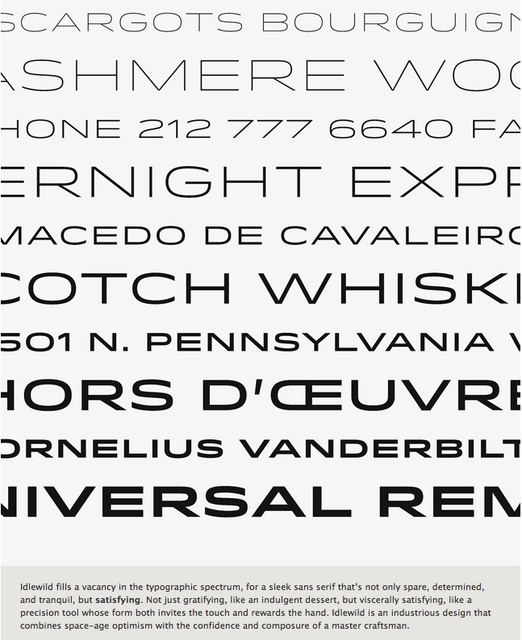
New Fonts from H&FJ: Idlewild
Außerdem finde ich es bedauerlich, das sie in Sachen Open Type Features auch nicht recht mit der Zeit gehen. Diesbezüglich sind die Schriften leider nur sehr schwach ausgebaut. Es gibt kaum alternative Buchstaben, geschweige denn Ziffernsätze etc. Und wenn bei der Idlewild unter Features neben der Sprachunterstützung lediglich andere Schriften zur Kombination angepriesen werden, ist das ja selbstredend.
Schade, denn ihre Schriften sind formal wirklich toll.
Außerdem finde ich es bedauerlich, das sie in Sachen Open Type Features auch nicht recht mit der Zeit gehen. Diesbezüglich sind die Schriften leider nur sehr schwach ausgebaut. Es gibt kaum alternative Buchstaben, geschweige denn Ziffernsätze etc.